2023 年春のベスト 32 フォント (無料およびプレミアム)
公開: 2023-09-21完璧なフォントを使用してプロジェクトのデザインをどのように向上させることができるか考えたことはありますか? このブログ投稿では、Spring フォントの世界と、Spring フォントがデザインをどのように変えることができるかを探っていきます。
あなたがグラフィック デザイナーであっても、プロジェクトの視覚的な魅力を高めたいと考えている人であっても、この記事はあなたのためのものです。
Spring Fonts は、デザインに新鮮さと活気を加える適切なタイポグラフィーを見つけることがすべてです。
季節の変わり目は、春の気分を反映したフォントを探すのに最適な時期です。 風変わりで遊び心のあるフォントからエレガントで洗練されたフォントまで、あらゆるスタイルやプロジェクトに合うフォントが存在します。
適切なフォントの選択が、プロジェクトの全体的なデザインとメッセージに大きな影響を与える可能性があることをご存知ですか?
さまざまな感情を呼び起こし、重要な情報を強調し、一貫した視覚体験を生み出すことができます。
春のフォントを使用すると、デザインに更新、成長、エネルギーの感覚を吹き込むことができます。 したがって、チラシ、Web サイト、ソーシャル メディアの投稿のいずれで作業している場合でも、春の本質を捉えるには、適切なフォントを選択することが重要になります。
この記事では、さまざまな Spring フォントを検討し、プロジェクトのデザインを強化する可能性を紹介します。
優雅さを醸し出す繊細な筆記体フォントから、注目を集める大胆でモダンな書体まで、クリエイティブなニーズに合わせた幅広いオプションが見つかります。 それでは、春のフォントの新鮮さと美しさを取り入れてみましょう!
最高のプレミアム Spring フォント
美しい春のフォントを使ってデザイン プロジェクトをリフレッシュしてみませんか? これ以上探さない! この記事では、あなたのデザインに優雅さと活気を確実に加える最高のプレミアム Spring フォントをまとめました。
では、これらの素晴らしいフォントをチェックして、あなたの創造力を開花させてみてはいかがでしょうか?
コロラド
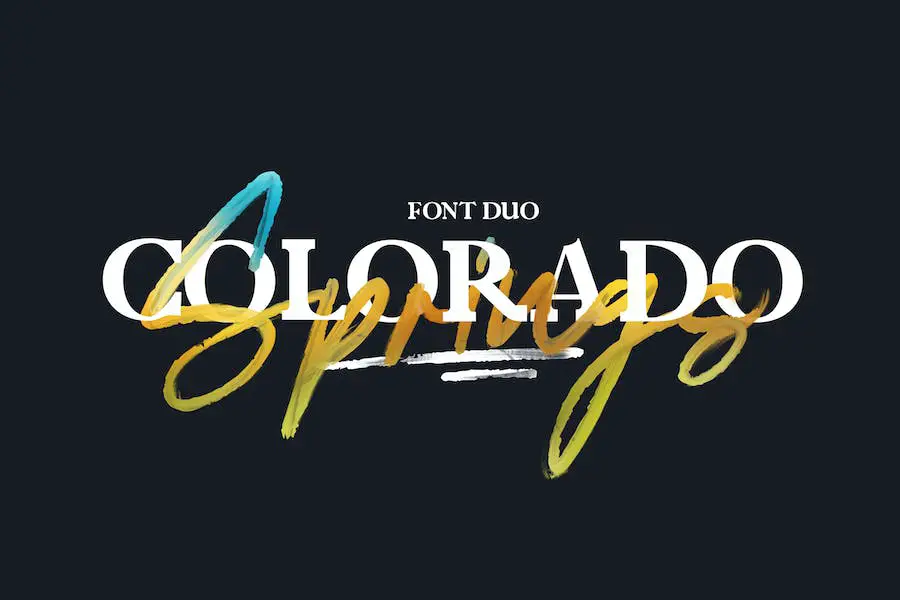
Colorado は、あなたのデザインを瞬時に次のレベルに引き上げるフォント デュオです。
見出し、タイトル、ポスター、本の表紙に最適で、レトロなフォントと力強い幾何学的な書体からインスピレーションを得たユニークなスタイルを誇ります。 特徴は、見た人の記憶に残る、完璧に凝縮されたフォルムです。
Colorado にはスタイリッシュな組み合わせのためのスクリプト フォントが付属しているだけでなく、この Google spring フォントもさまざまなアプリケーションに適しています。
テキスト、印刷物、ユーザー インターフェイス、モバイル デバイス、Web デザイン、ポスターなどを表示する必要がある場合は、このフォントが対応します。 あらゆるレイアウトでデザインを強化する最適な文字のセットを提供します。
Colorado を使用すると、プロジェクトを目立たせ、永続的な印象を残すことができます。 その多用途性と独特のスタイルにより、自分の作品を向上させたいグラフィック デザイナーにとって必須のツールとなっています。
さわやかな春
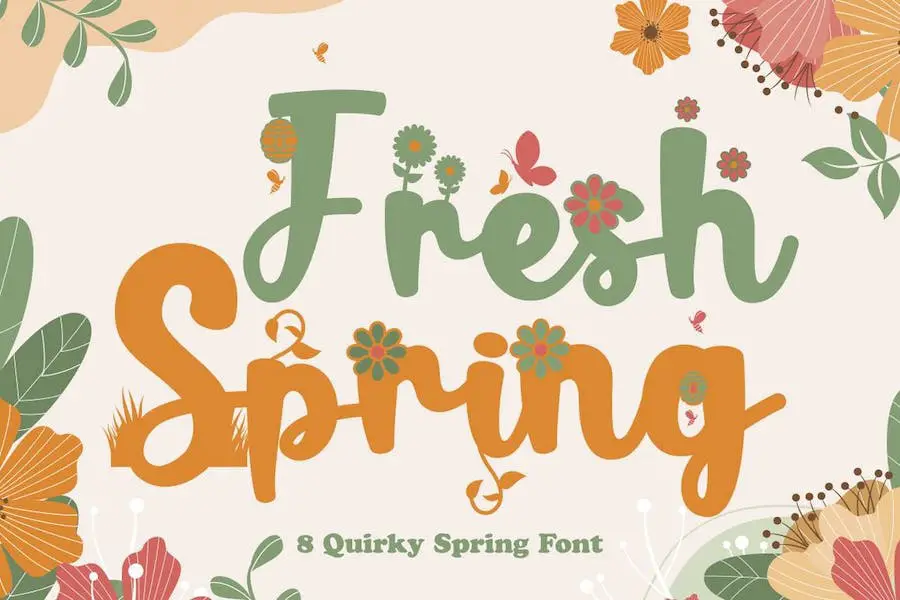
Fresh Spring – 8 Quirky Spring Font は、7 つの異なるバージョンを提供するユニークな植物フォントで、それぞれに独自の植物の装飾が施されています。
この Adobe spring フォントは、柔らかくて楽しいことが特徴で、取り組んでいるプロジェクトに合わせてさまざまな形やオプションが用意されています。
愛、植物、子供、赤ちゃん、結婚式をテーマにしたプロジェクトであっても、このフォントはあなたをサポートします。
それだけでなく、招待状、グリーティング カード、ロゴ、ブランディング、ポスター、クラフト、ステッカー、ソーシャル メディア、パッケージ、ヘッダー、商品などにも最適です。可能性は無限大です。
ガーデン ウェディングの招待状を作成している場合でも、植物苗床のロゴをデザインしている場合でも、持続可能な生活についてのソーシャル メディア投稿を作成している場合でも、Fresh Spring – 8 Quirky Spring Font は、春のエッセンスを捉え、デザインに命を吹き込むのに役立ちます。 。
野の花
Wildflowers は、「It In Spring – Sans Font」と「It In Spring – Script Font」という 2 つのユニークで美しいフォントが含まれるフォント パッケージです。
Wildflowers を使用すると、プロジェクトのデザインを簡単に改善し、魅力的で視覚的に魅力的な美学を作成できます。
スプリングス
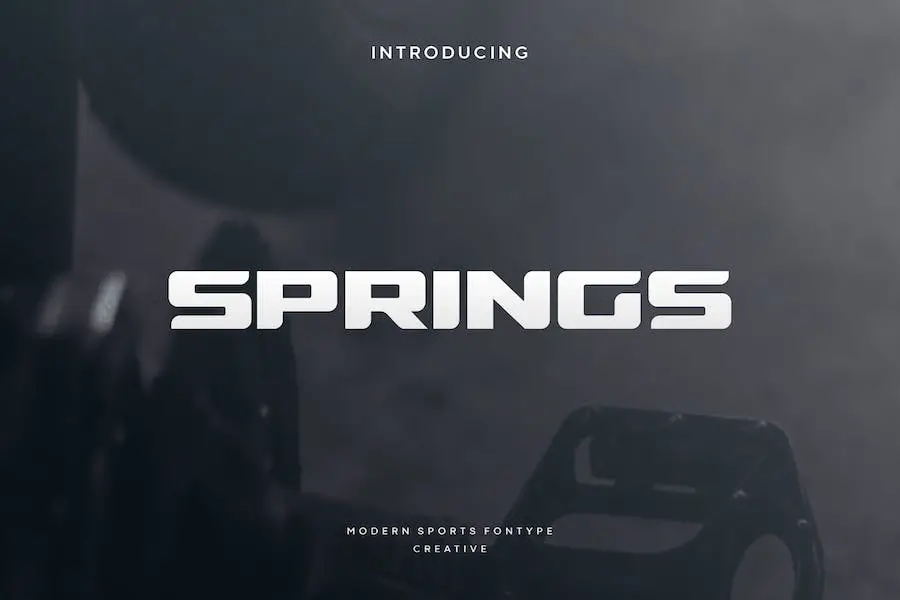
Springs は、フォーマルなスタイルと遊び心のあるスタイルをシームレスに融合させた、ユニークでモダンな表示フォントです。 独特の魅力を持つこのフォントは、デザイン プロジェクトに無限の可能性をもたらします。
日曜日の春
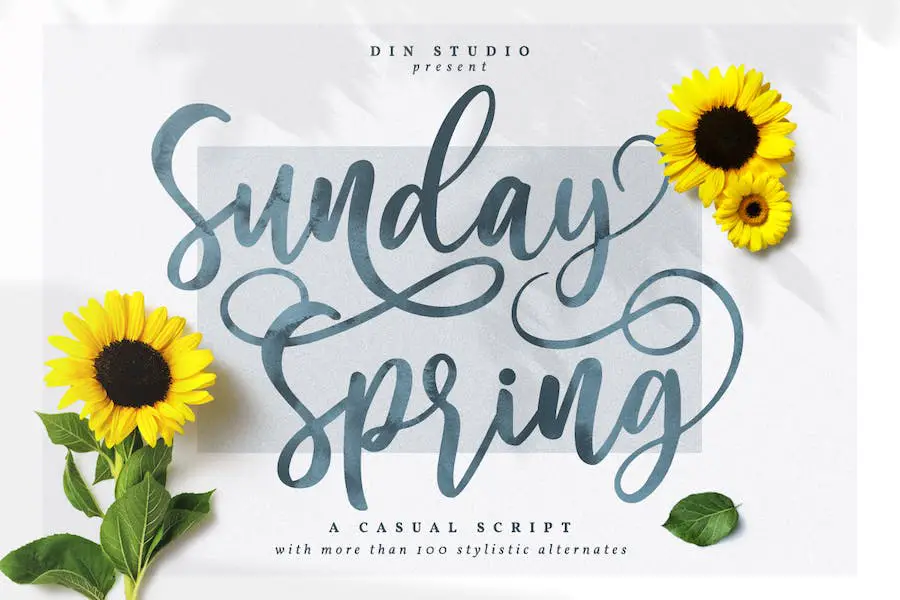
Sunday Spring は、デザイン プロジェクトに美しさを加える素晴らしいブラシ フォントです。
天然のハンドブラシを使用して作成されたこの Spring Fonts for Cricut フォントは、ブランディング、ファッション スタイル、印刷テンプレート、引用符、さらには結婚式など、さまざまなデザイン目的に最適です。
春の時間
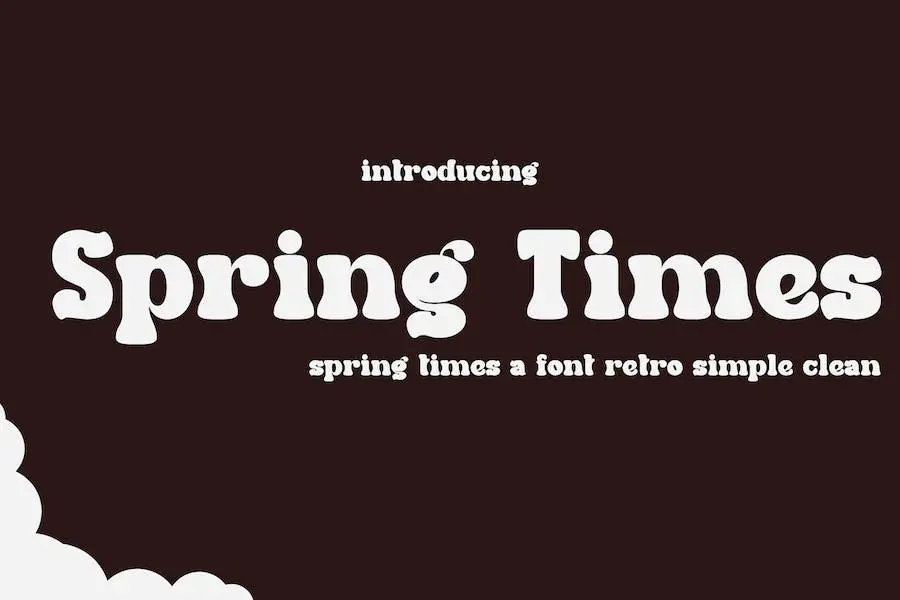
Spring Times は、あらゆるプロジェクトにレトロなスタイルを加える魅力的で大胆なフォントです。
柔らかくくっきりとしたデザインで、美しく高級感を演出するのに最適なフォントです。
ロゴ、Web サイト、またはその他のクリエイティブなプロジェクトをデザインしている場合でも、この Spring Fonts for Tattoo を使用すると、デザインがすぐにより魅力的で大胆になります。 試してみて、その違いを確認してください。
魔法の泉
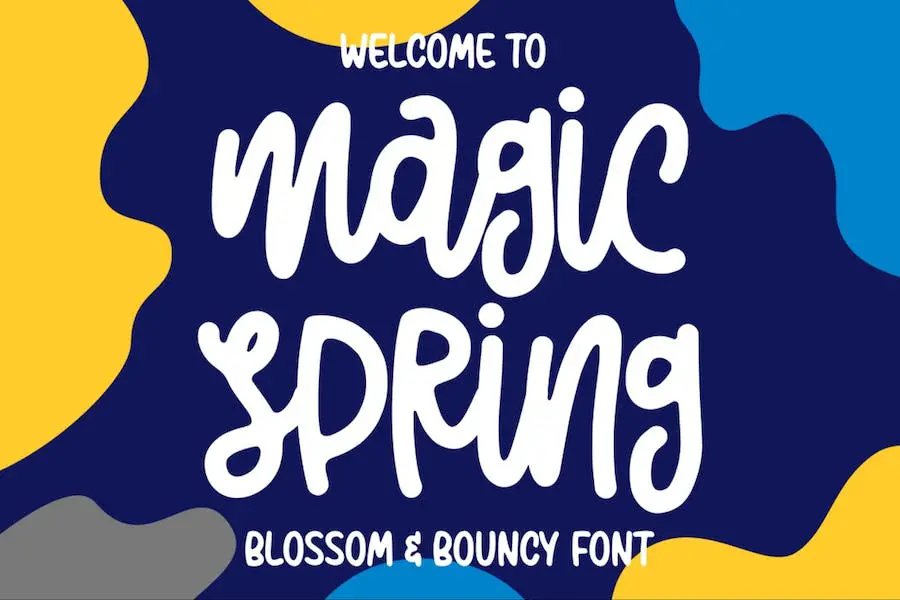
Magic Spring は、プロジェクトのデザインを強化したいグラフィック デザイナーに最適な多用途フォントです。 この Spring Posters フォントは、作品に自然の美しさをもたらすように細心の注意を払って作成されています。
Magic Spring は、大胆なペン先とペンをイメージしたスタイルで手書きの魅力の本質を捉え、ロゴ デザイン、ブランド イメージ、引用文、製品パッケージ、商品、ソーシャル メディアの投稿に本物らしさを加えます。
Magic Spring を使用してプロジェクトに自然とスタイルのタッチを追加し、作品が芸術作品に変わる様子を観察してください。
春の願い
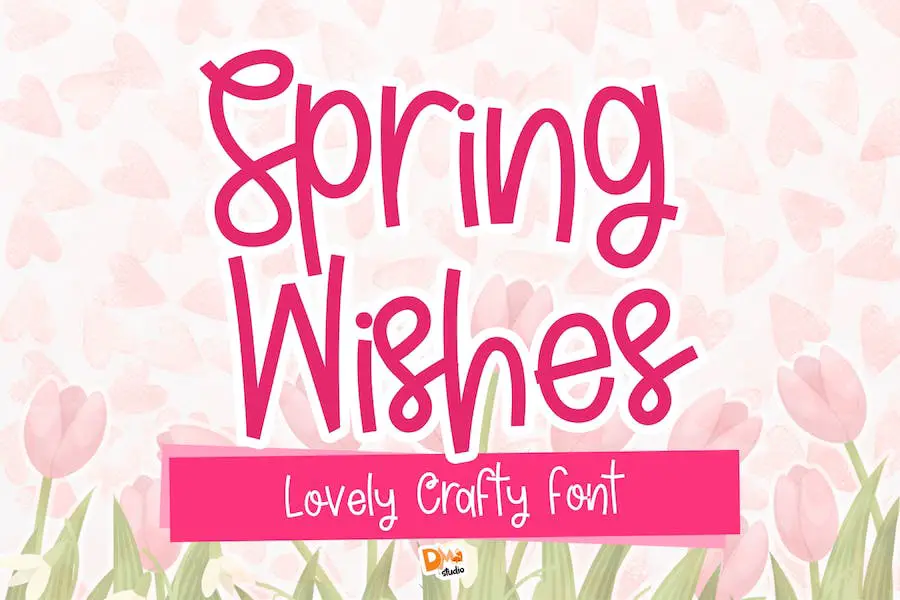
Spring Wishes は、デザイン プロジェクトを強化するためのさまざまな機能を提供する魅力的で多用途なフォントです。
大文字、小文字、数字、記号、多言語サポートを備えたこのフォントには、美しく魅力的なコンテンツを作成するために必要なものがすべて揃っています。
バレンタインデーのプロジェクト、DIY クラフト、またはソーシャル メディアへの投稿に取り組んでいる場合でも、Spring Wishes は完璧な選択です。
その風変わりで愛らしいスタイルは、どんなデザインにも奇抜なタッチを加え、創造性を表現し、愛を広めるのに最適です。
どのような言語を扱う必要があるとしても、このデザイナー向け Spring フォントで対応できます。 多言語サポートにより、このフォントをさまざまな言語要件を持つプロジェクトに簡単に組み込むことができます。
春のデザート
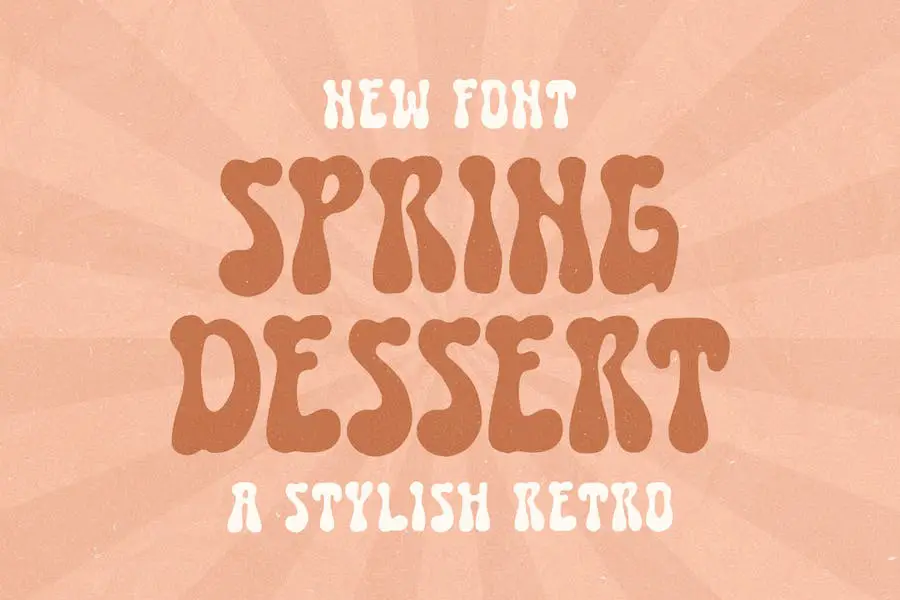
Spring Dessert は、陽気なタッチのスタイリッシュなレトロなフォントです。 デザインに楽しくて遊び心のある要素を追加するのに最適です。
ロゴ、招待状、ラベル、雑誌のレイアウト、またはあらゆるタイプの広告に取り組んでいる場合でも、このフォントはプロジェクトを向上させ、目立たせることができます。Spring Fonts Generator は必要ありません。
Spring Dessert の大きな特徴の 1 つは、その多用途性です。 大文字と小文字の両方で使用でき、数字と句読点もサポートされます。
つまり、制限なくユニークで目を引くデザインを作成できます。 さらに、このフォントは多言語に対応しているため、さまざまな言語で使用でき、より幅広いユーザーに届けることができます。
さらに、Spring Dessert は PUA でエンコードされています。 PUA は Private Use Area の略で、OpenType 機能をサポートしていないプログラムでもフォントに簡単にアクセスして使用できるようにします。 これは、好みのデザイン ソフトウェアに関係なく、フォントを手間なく使用できることを意味します。
こんにちは春
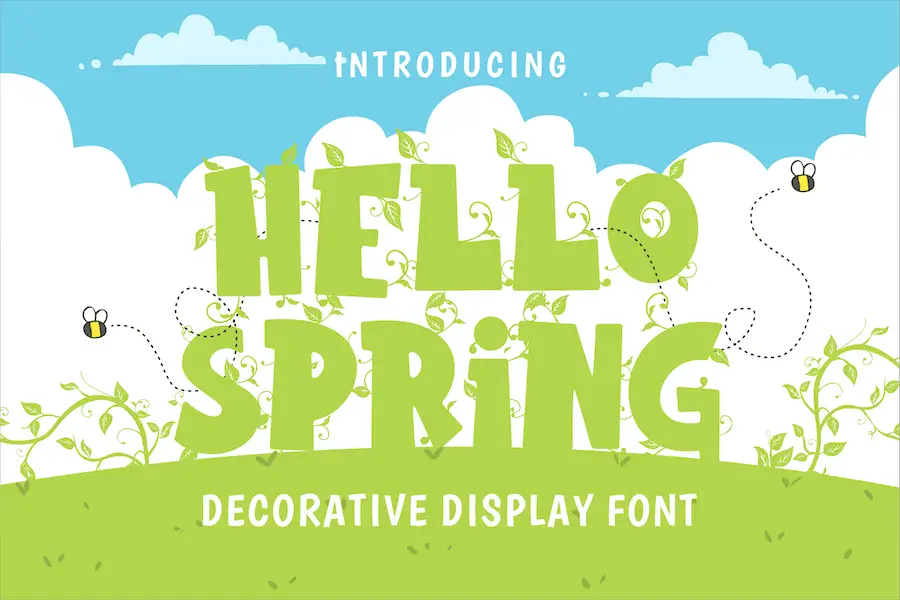
Hello, Spring は、新しい季節の活気に満ちたエネルギーと暖かさからインスピレーションを得た装飾的な表示フォントです。
Spring Handwriting フォントはそのユニークな特徴により多用途で、引用文、T シャツのデザイン、チラシ、YouTube チャンネル、ラベル、ロゴなど、幅広い目的に使用できます。
遊び心のある魅力的なデザインは、あらゆるプロジェクトに春の魅力を加え、新鮮で季節感のあるデザインを強化したいグラフィック デザイナーにとって必須のアイテムです。
ひまわりの春
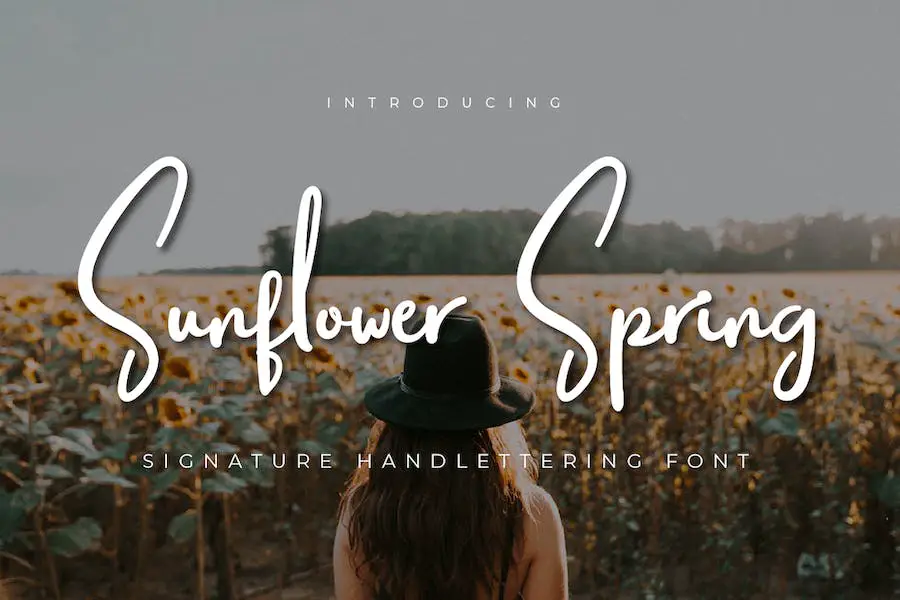
結論
要約すると、この記事では、グラフィック デザイナーがデザインを強化するためにダウンロードして使用できる、いくつかの美しい Spring フォントを検討しました。 私たちはフォント選択の重要性と、適切なフォントがどのようにプロジェクトに新鮮で活気のあるタッチを加えることができるかについて話し合いました。